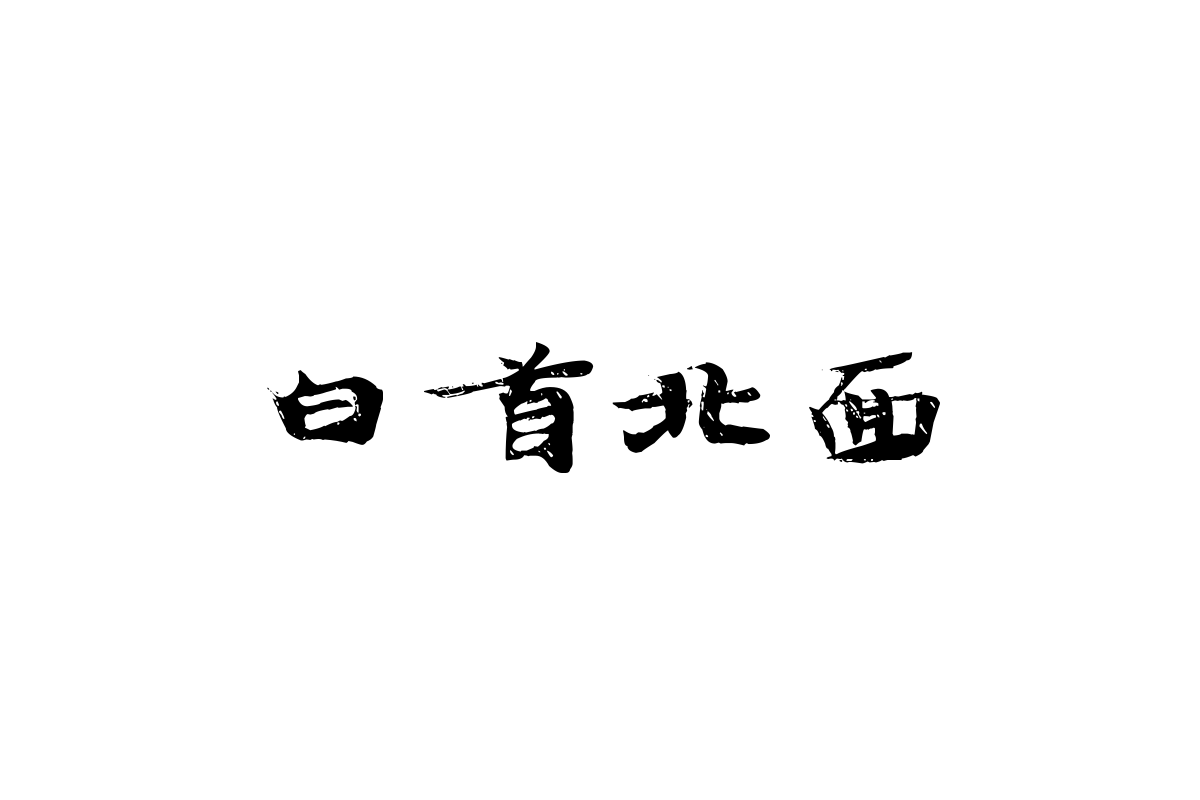
汉仪新蒂春联体是一款具有现代感和艺术气息的中文字体,适用于各种印刷品、广告、设计等领域。这款字体的特点是线条流畅、结构紧凑、字形美观大方,给人一种清新、自然的感觉。
字体特点:
1. 线条流畅:汉仪新蒂春联体的笔画线条流畅,没有过多的装饰性线条,给人一种简洁、明了的感觉。
2. 结构紧凑:字体的结构紧凑,字形大小适中,适合用于各种尺寸的印刷品。
3. 字形美观大方:字体的字形美观大方,既有传统书法的韵味,又有现代设计的美感,适合用于各种场合。
4. 易于识别:字体的字形规整,易于识别,方便设计师进行文字设计。